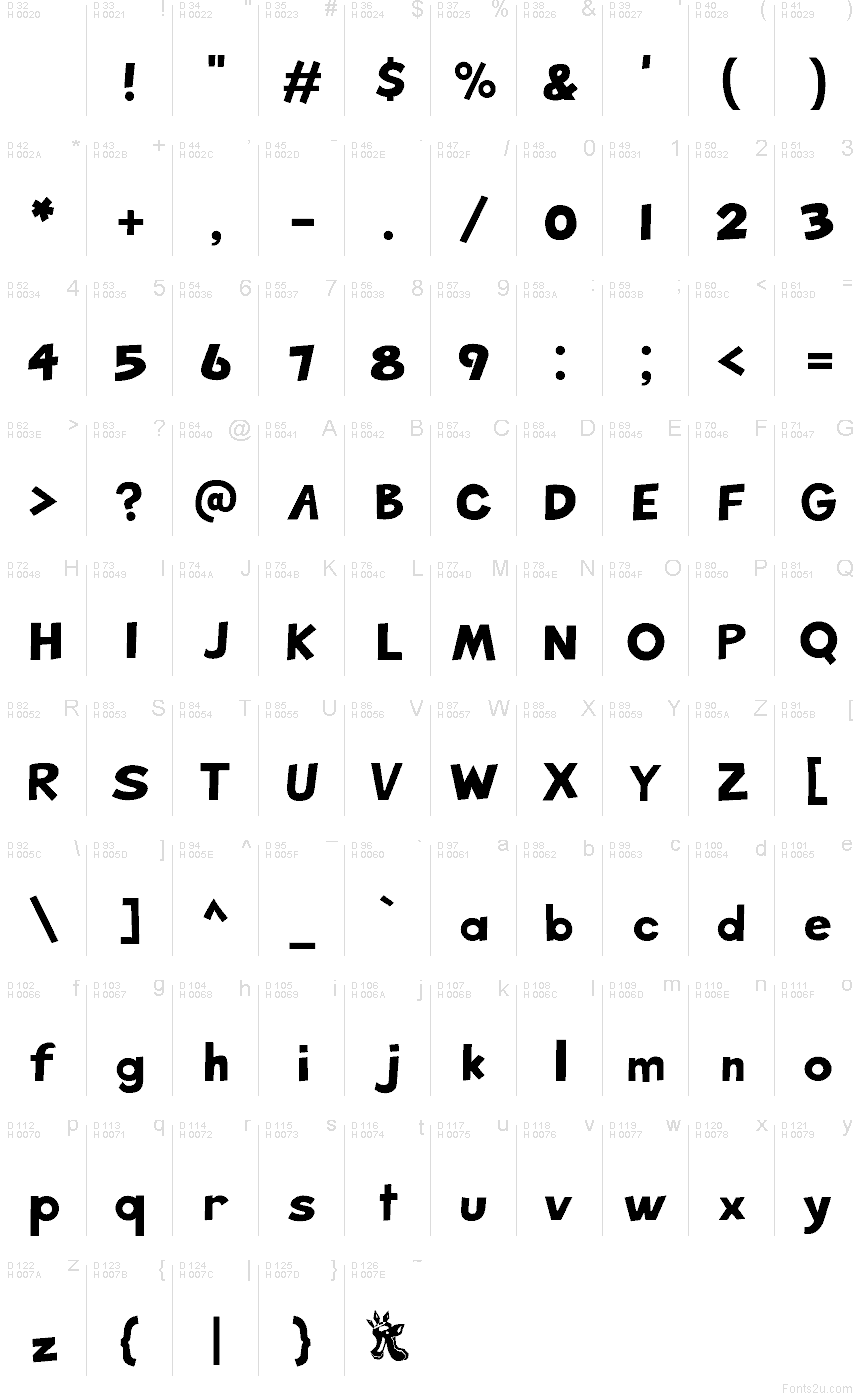
Twister Refusion, di Elise Benoit, è un font display gratuito in stile fumetto caratterizzato da un ritmo intenzionalmente distorto e fuori asse. Le lettere si inclinano, ondeggiano e si gonfiano in modo artigianale e leggermente indisciplinato; le forme massicce e le giunture affilate donano un tocco più grezzo al suo spirito giocoso.
È perfetto per i titoli di poster, copertine di fanzine, volantini per eventi per bambini, titoli di fumetti indie e packaging che richiedono una voce vivace e animata. Essendo un font gratuito, funziona al meglio dove serve carattere immediato: la cadenza irregolare e le variazioni di peso conferiscono un tocco dinamico e improvvisato a titoli brevi, linee di copertina e loghi.